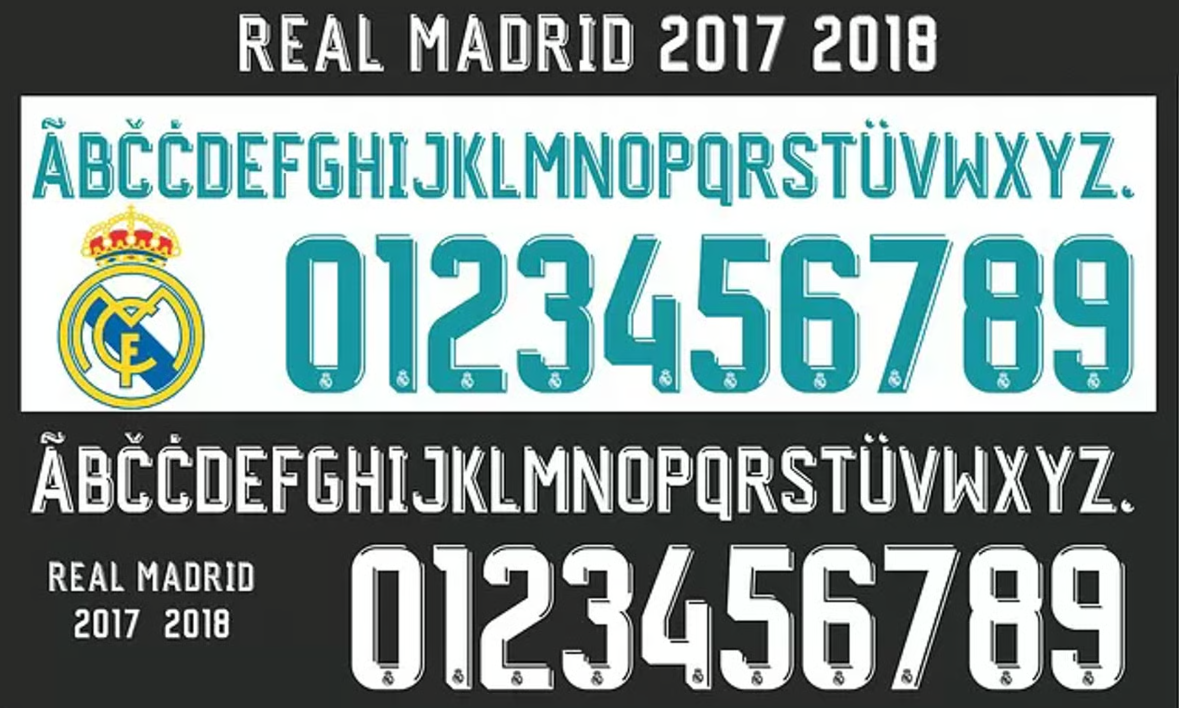
Se existe uma camisa que carrega peso histórico, é a do Real Madrid da temporada 2017/2018. Foi com este uniforme, marcado pelos detalhes em azul turquesa sobre o branco clássico, que o clube merengue conquistou sua 13ª Champions League (La Decimotercera) em Kiev.
Neste post, trazemos para você a fonte oficial utilizada pela Adidas nas competições europeias e copas daquela temporada. É a tipografia exata usada por lendas como Cristiano Ronaldo, Sergio Ramos e Modrić em um dos anos mais vitoriosos da história do clube.
- Conteúdo: Alfabeto completo e numeração oficial (com o logo do clube na base do número, se aplicável na versão vetorial).
Estilo Visual e Identidade
A tipografia criada pela Adidas para o Real Madrid nesta temporada fugiu do padrão. Diferente das fontes clássicas e rígidas, esta fonte apresenta um estilo moderno, levemente arredondado e com uma pegada “digital” irregular.
Ela foi desenhada para contrastar com a elegância sóbria do uniforme branco, trazendo um ar de juventude e inovação. É importante notar que esta fonte específica foi usada na UEFA Champions League e na Copa do Rei. Na La Liga, o clube utilizou a fonte padronizada da competição, mas a versão que todo torcedor deseja ter é esta: a da glória europeia.
Dica de Especialista: Ao aplicar esta fonte em fundos escuros (como no uniforme 2, preto, daquela temporada), utilize a cor “Turquesa Neon” para manter a fidelidade ao kit original de jogo.